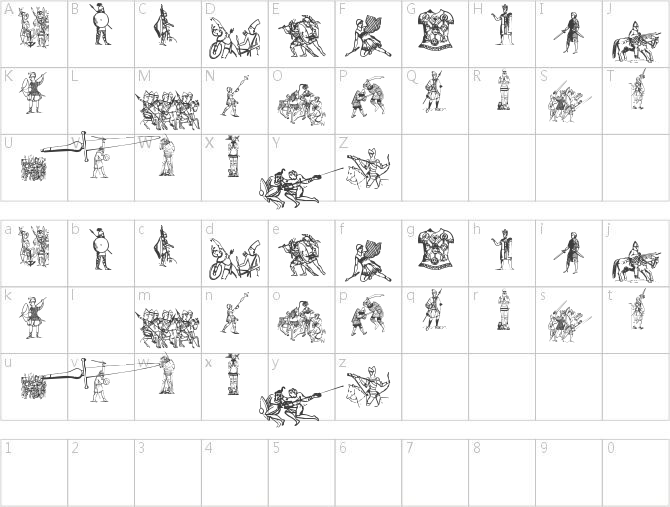
字體名稱: Ancient
Ancient warriors and weapons tfb
Ancient warriors and weapons tfb字體字庫是一款讓人賞心悅目、百看不厭的英文字體,適合各類廣告和產品包裝設計應用,字體大小0.42MB,格式為ttf字體,上傳用戶是東方時尚,作者/版權方為未知